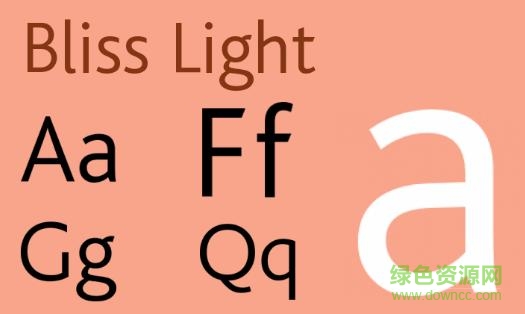
bliss light字體是一款表現(xiàn)力不錯(cuò)的英文無(wú)襯線字體,字體結(jié)構(gòu)舒展柔和,字符節(jié)奏感強(qiáng),易于辨識(shí)和閱讀,視覺體驗(yàn)良好,有需要的朋友快來(lái)綠色資源網(wǎng)下載吧!
英文字符的間距要比它的外形重要得多,這關(guān)系到英文創(chuàng)意字體設(shè)計(jì)的節(jié)奏。一種間距很糟糕的英文字體,不管外形如何優(yōu)美,一樣難于閱讀。相反的,一款外形稍欠的字體,如果有完美的間距調(diào)節(jié),這種字體一樣可以易于閱讀。因此,定義字體的節(jié)奏,要比定義英文美術(shù)字體的外形更加重要。
1.有襯線的字體叫襯線體(serif);沒有襯線的字體,則叫做無(wú)襯線體。
2.無(wú)襯線字體又可以分為無(wú)襯線幾何體、無(wú)襯線人文體、無(wú)襯線新粗黑體。